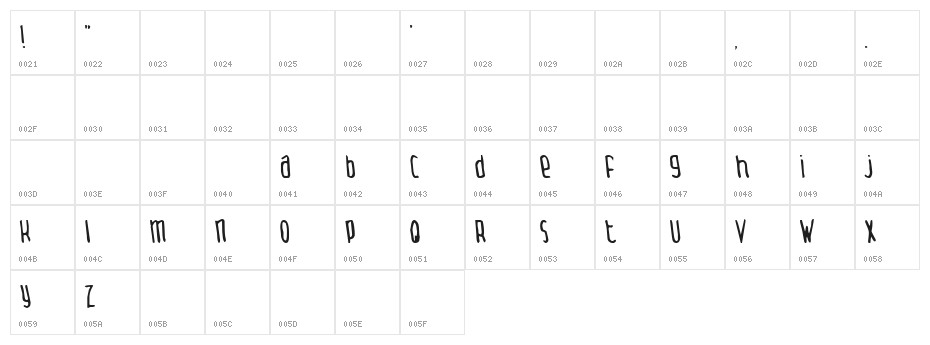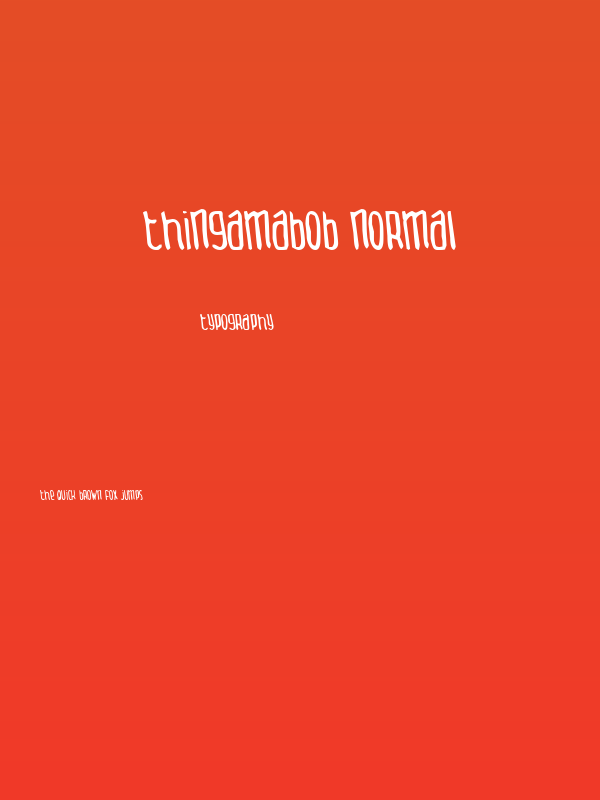
Thingamabob Normal Font
| Stil general | Playful, Quirky, Hand-drawn |
| Proiecte propuse | Ideal for children's books, creative posters, playful branding, and informal invitations. |